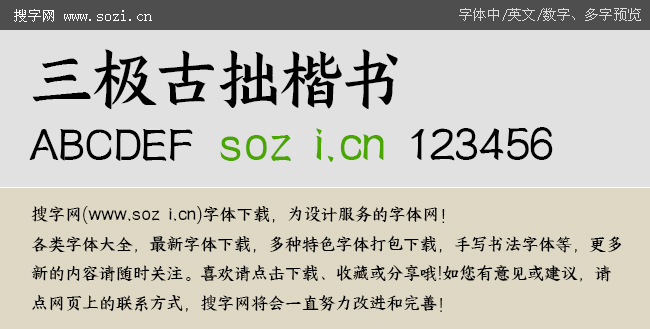
三極古拙楷書
搜字網(wǎng)給大家提供一款三極古拙楷書中文字體下載,三極古拙楷書以現(xiàn)行楷書為基礎(chǔ),筆畫分明利落,字形端正,結(jié)構(gòu)嚴(yán)謹(jǐn),肅穆古拙,中宮偏大。起筆收筆樸拙有力,整體大巧若拙,寓巧于拙,盡顯樸拙之美。適用于平面宣傳設(shè)計(jì)、網(wǎng)頁(yè)設(shè)計(jì)、海報(bào)設(shè)計(jì)等應(yīng)用。